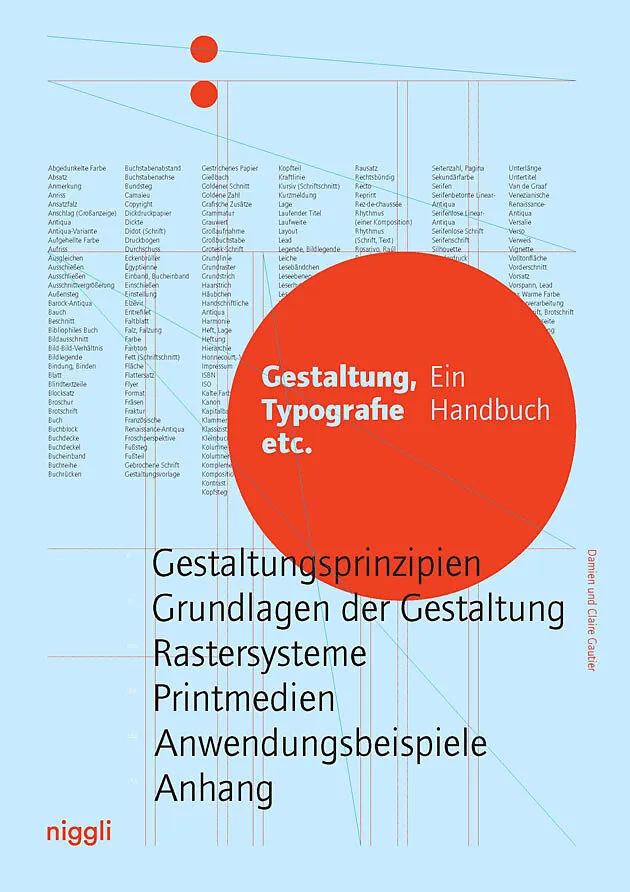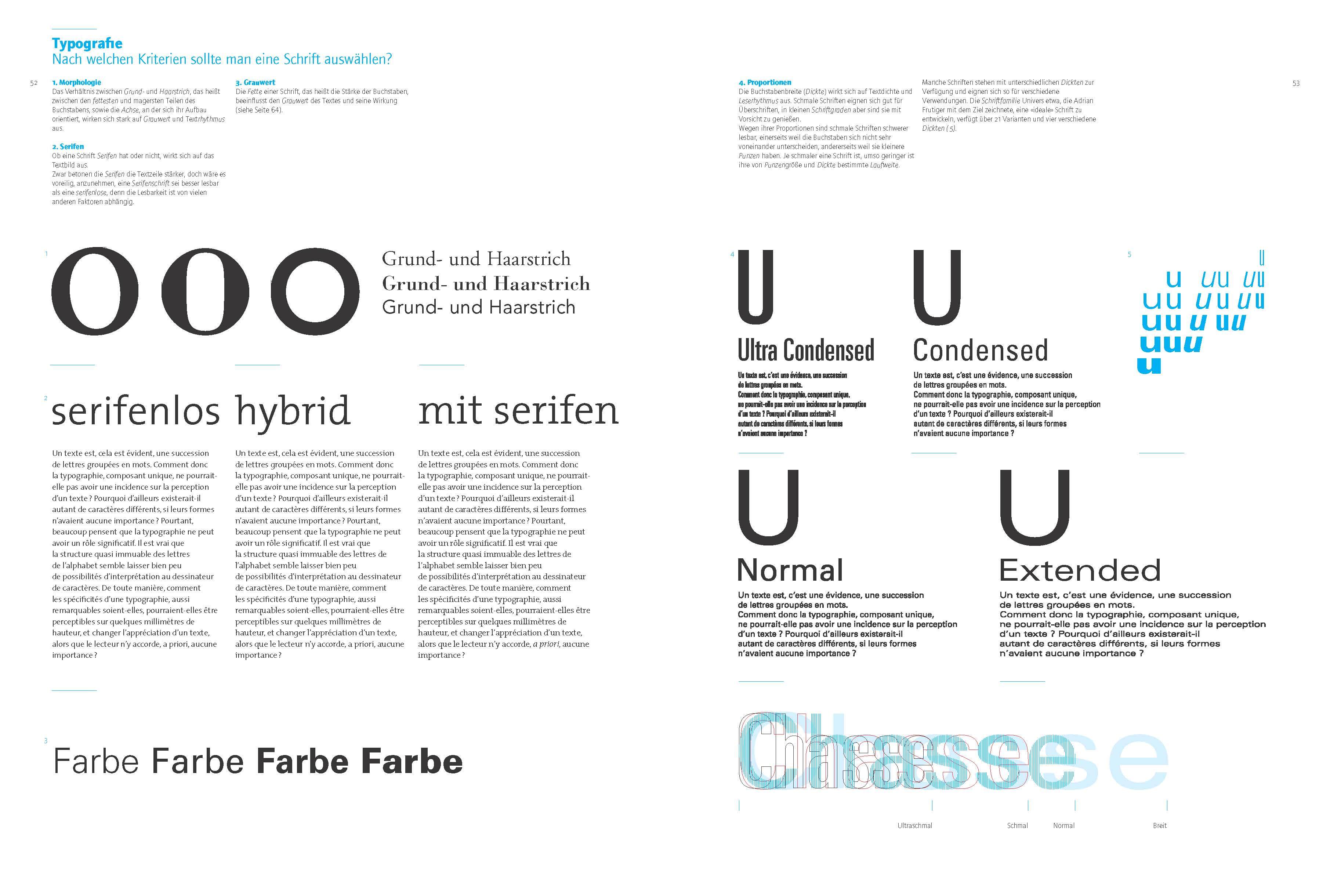
Gestaltung, Typografie etc.
Warum sieht eine Zeitung anders aus als eine Zeitschrift oder ein Buch? Welche Auswirkungen hat die Verwendung einer bestimmten Schrift, welche die eines bestimmten Rasters? Und warum wirkt das eine Layout ausgesprochen passend und uberzeugt und ein anderes ei...